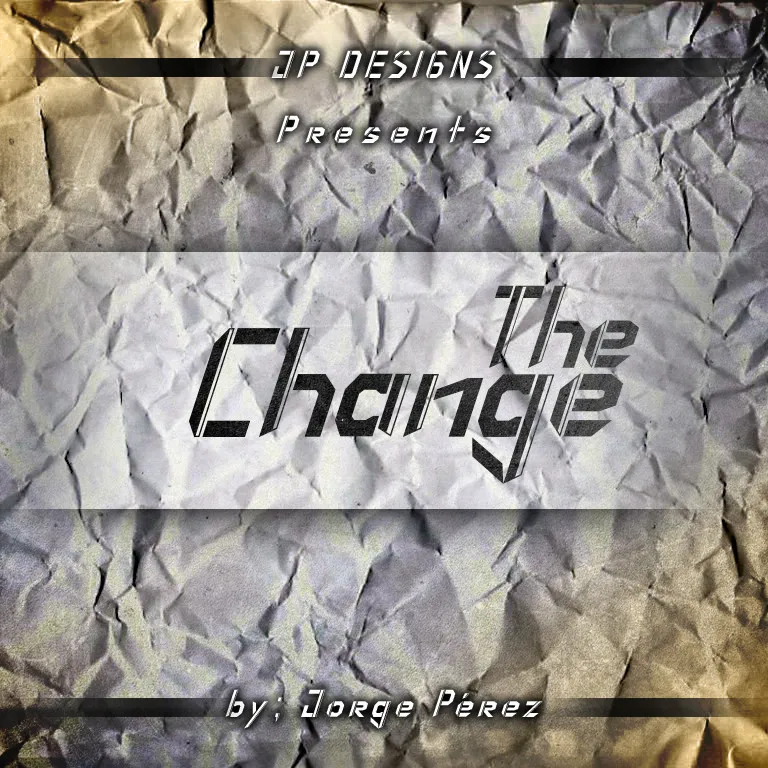
The Change Font
A fonte The Change é uma escolha perfeita para stencil designs criativos e modernos. Criada pelo designer Hamilton, esta fonte oferece uma linguagem única que se adequa perfeitamente ao estilo stencil, tornando-a ideal para projetos de arte urbana ou design gráfico experimental. Com letras, números e símbolos totalmente liberados em seu catálogo, a The Change Font não apenas atende às suas necessidades criativas, mas também permite-lhe explorar novas formas de expressão visual. Para facilitar o acesso à versão comercial que contém esses elementos bloqueados, basta entrar em contato diretamente com os responsáveis ​​via  e . A The Change Font não apenas traz um toque diferente aos seus projetos, mas também oferece a oportunidade de expandir seu vocabulário gráfico. Não perca tempo, explore agora a The Change Font para adicionar uma nova dimensão à sua arte digital ou impressa.